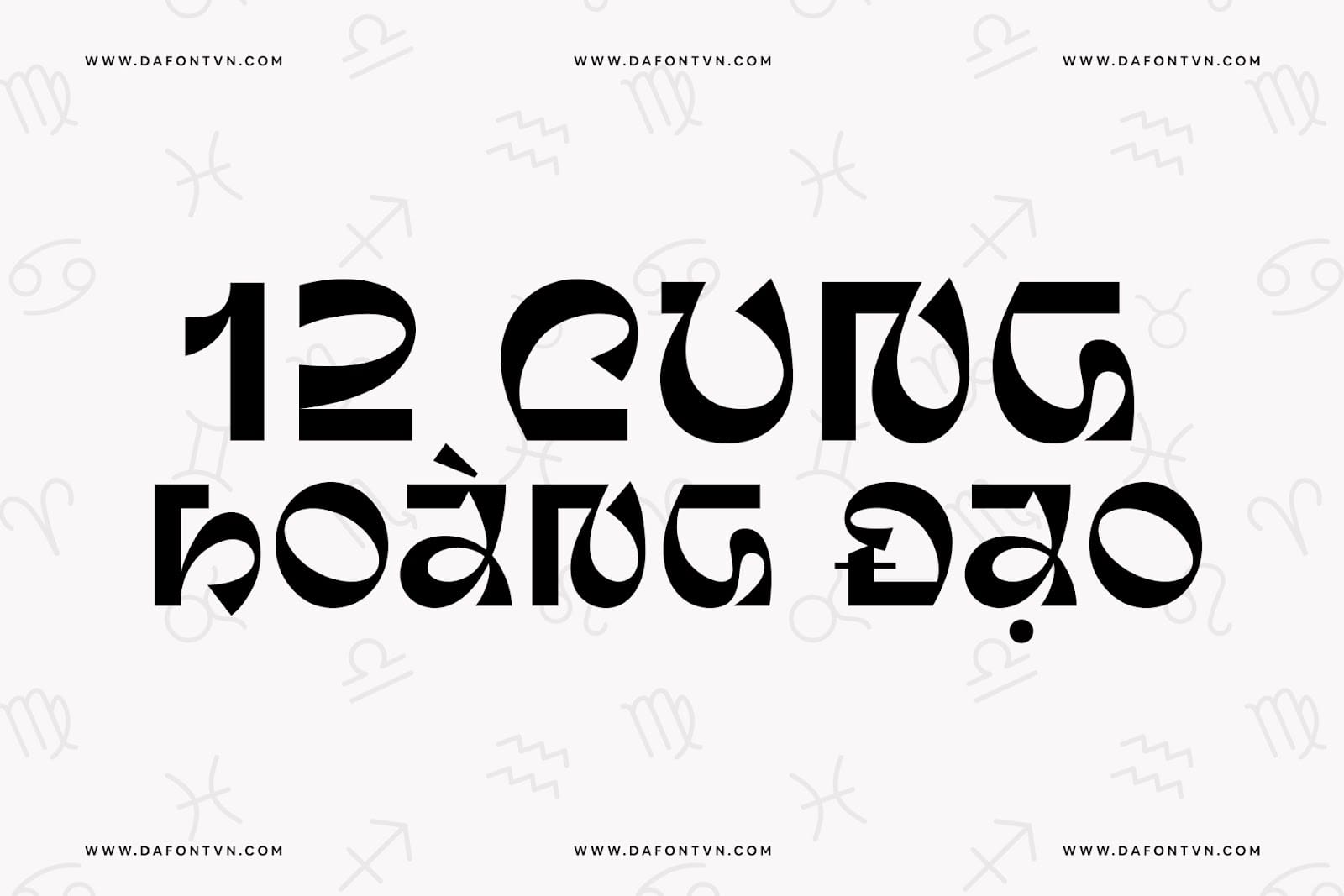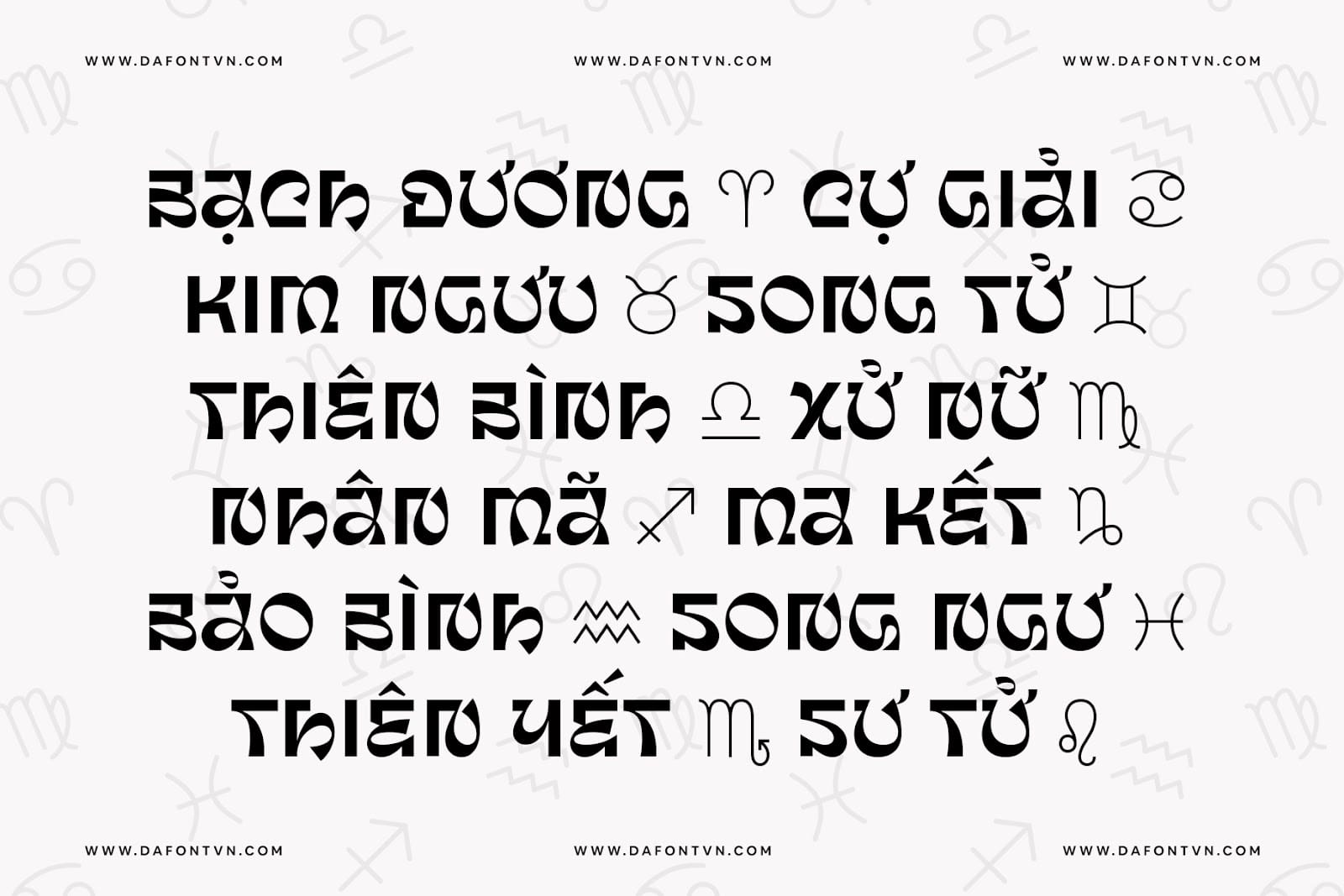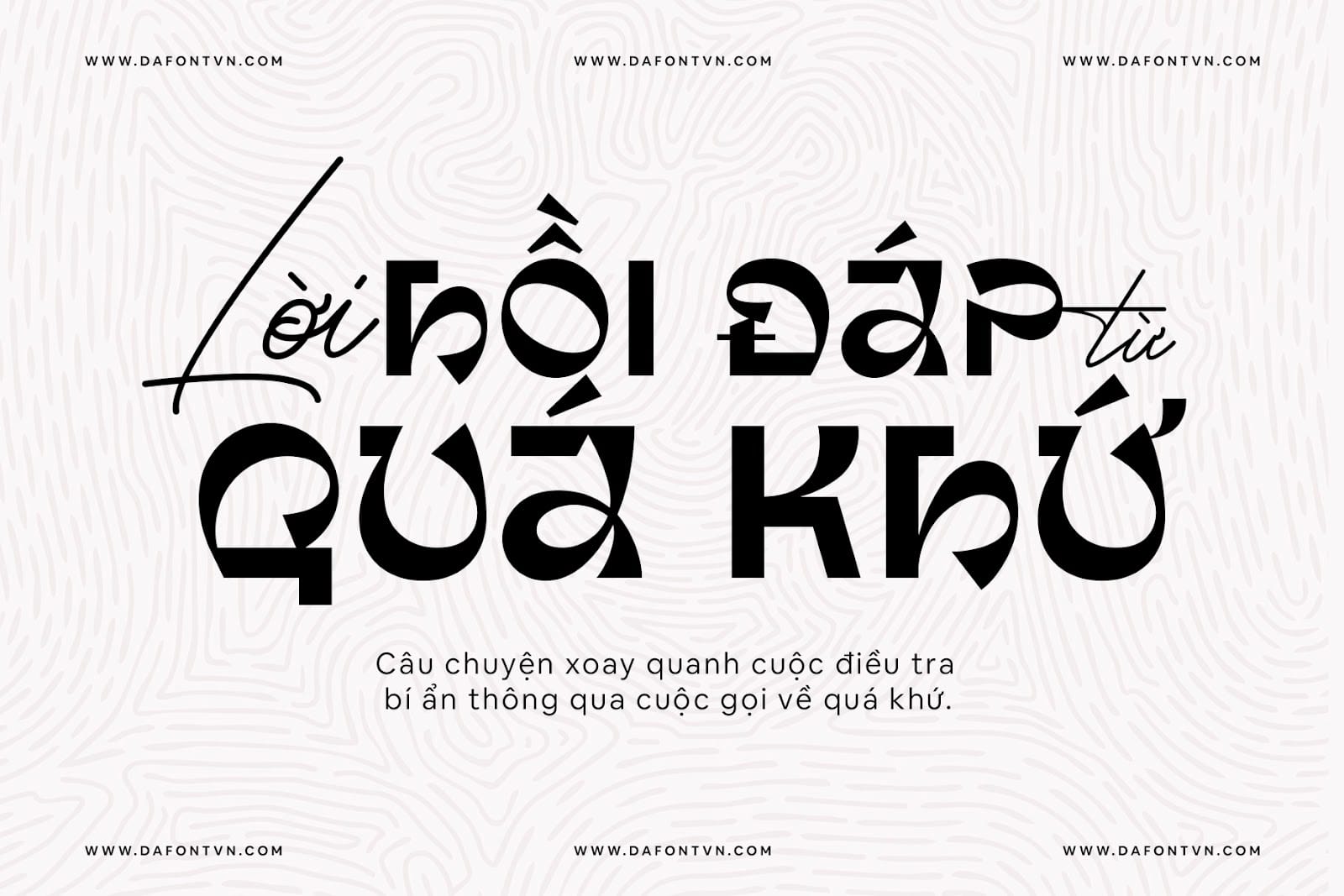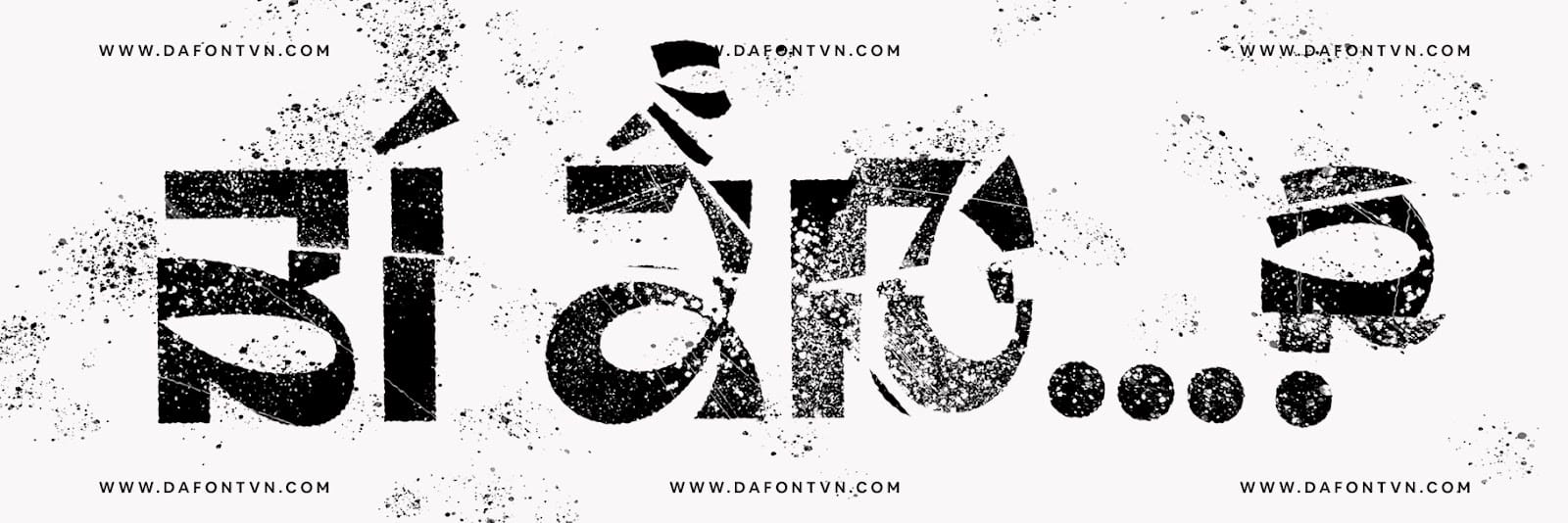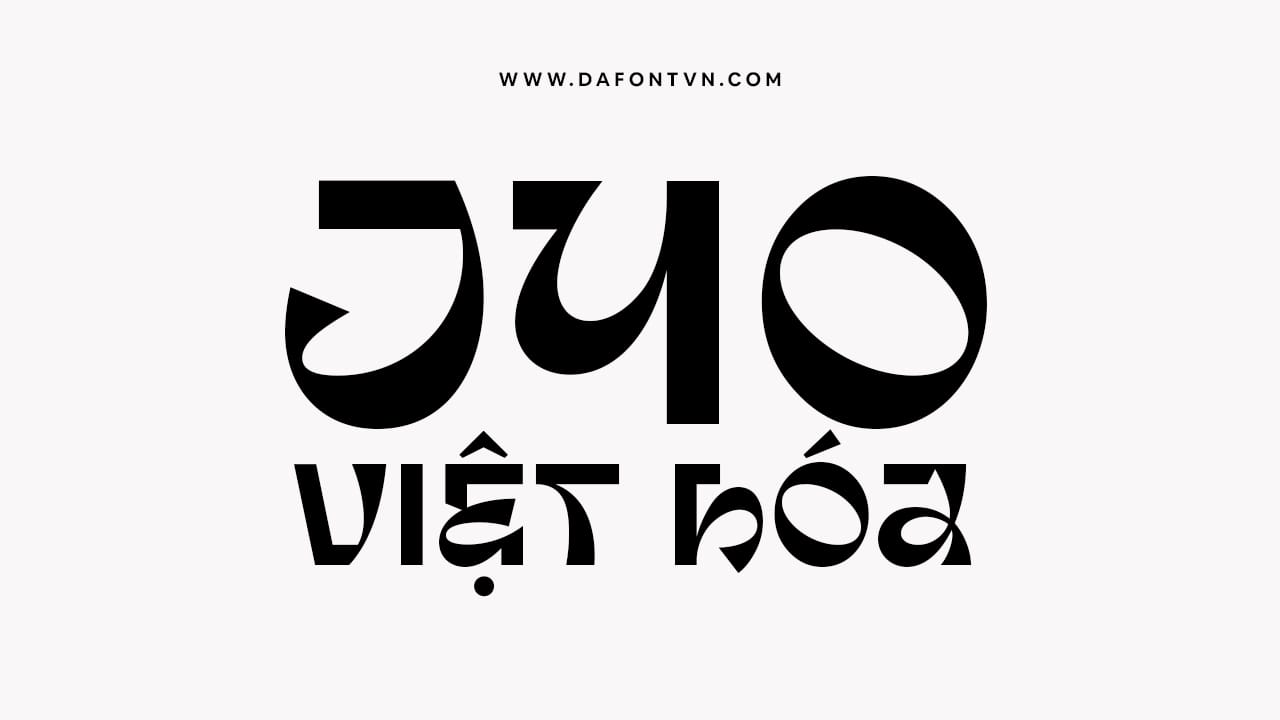
Jyo Display được lấy cảm hứng từ các tác phẩm cổ xưa của Ấn Độ và Jyotish, còn được gọi là chiêm tinh học Hindu. Nó thể hiện tính hai mặt giữa karma và tự do, cùng với sự tương phản của những hình khối cứng cáp và các nét cong vút trong văn bản tiếng Phạn cổ.
Kết quả là một kiểu chữ hiển thị thể hiển sự hài hòa của những đối lập thông qua sự tương phản giữa kiểu chữ không chân và những đường nét thư pháp một cách cân bằng hoàn hảo. Sự đối lập giữa thanh tao và trần tục.
Jyo Display mang lại cảm giác bí ẩn và độc đáo. Nó táo bạo và tinh tế theo cách riêng của nó – hoàn hảo để áp dụng cho những thiết kế như làm nổi bật tiêu đề. Ngoài ra font chữ còn bao gồm 1 số biểu tượng mặt cười, ký hiệu chiêm tinh và biểu tượng cung hoàng đạo.